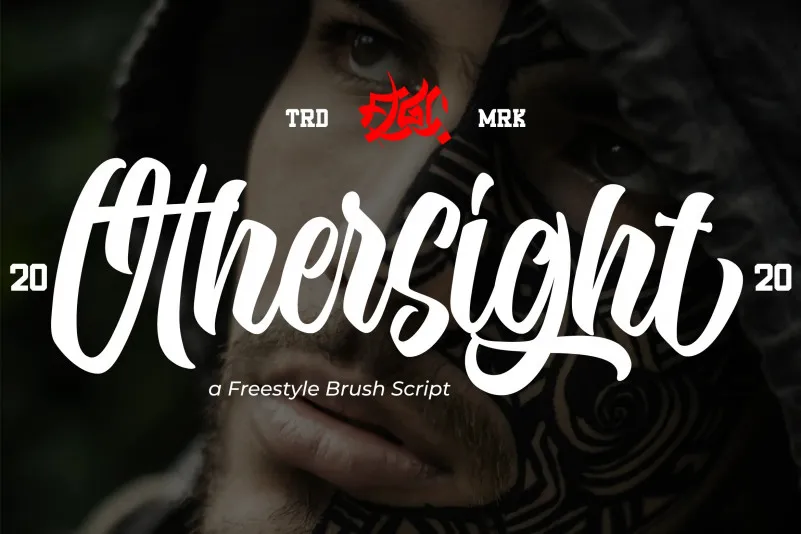
Othersight Script Font – Download Grátis
A Othersight Font é uma tipografia freestyle feita a mão inspirada nos anúncios clássicos. Seu estilo é naturalmente autêntico, remetendo diretamente ao design de letras escritas à mão. É perfeito para quem procura um recurso que transforme qualquer projeto em algo ainda mais belo e poderoso. Ideal para criações como cartazes, logotipos ou projetos pessoais, ela também é ótima para trabalhos de apparel, signatários personalizados, capas de álbum, editoriais digitais e mídias sociais. Além disso, a Othersight Font não só enriquece seu design, mas também o torna único e autêntico. É uma fonte que todos os amantes de design devem ter no seu arsenal.